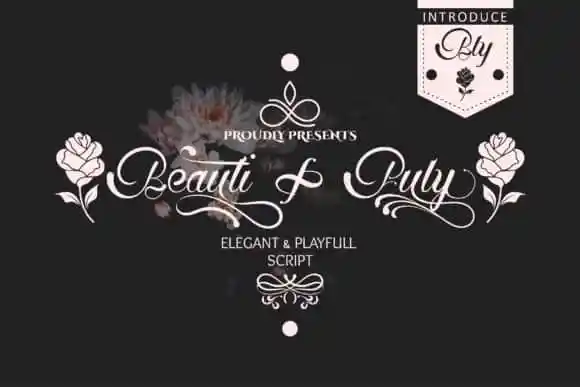
Beautifuly Calligraphy Font – Fonte Grátis
Beautifuly Calligraphy Font
A Beautifuly Calligraphy Font é uma nova tipografia escrita feita para várias finalidades, como logomarcas, convites de casamento, camisetas, cartas de boletim, sinais, rótulos e muito mais! Esta fonte de tipo círculo é do designer Prast Art. É um fonte script incrível. Ela apresenta desenhos únicos de pontilhados e ligaduras que tornam este estilo de escrita extremamente versátil. Inspire-se em seu estilo autêntico e use-o para criar convites de casamento exuberantes, arte de papelaria encantadora, posts atraentes nas redes sociais e cartas de cumprimentos fofas.